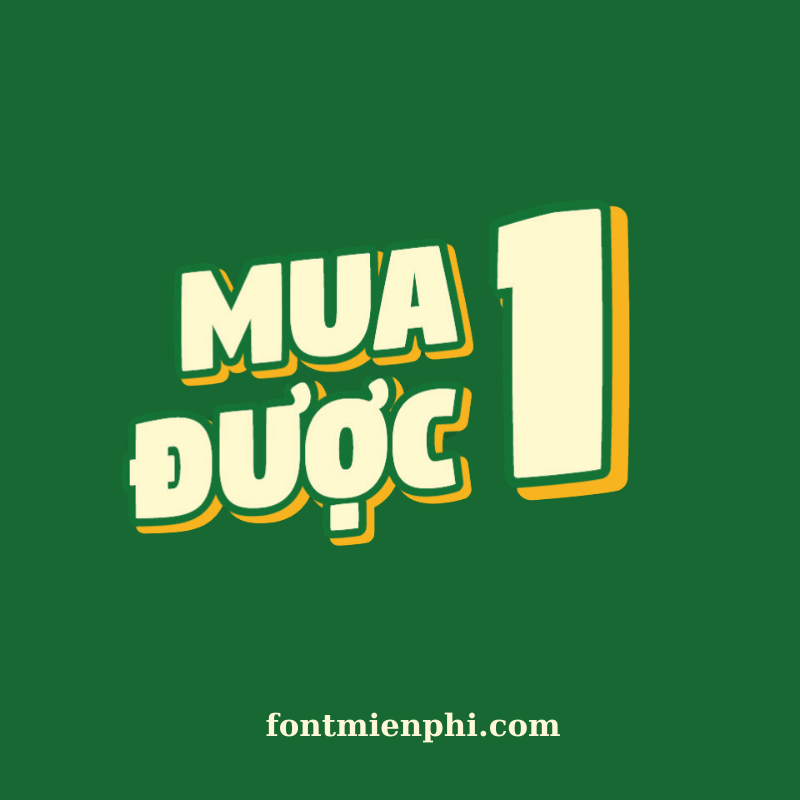
Font Việt hóa 1FTV VIP Digitalt
Font Việt Hóa 1FTV VIP Digital – Phong Cách Độc Đáo Cho Thiết Kế
Giới Thiệu
Font Việt hóa 1FTV VIP Digital là bộ font chữ cao cấp, được thiết kế tinh tế với khả năng hỗ trợ tiếng Việt đầy đủ. Với phong cách hiện đại, đa dạng kiểu chữ, font này phù hợp cho nhiều dự án sáng tạo như thiết kế đồ họa, quảng cáo, in ấn và digital marketing.
Đặc Điểm Nổi Bật
• Hỗ trợ tiếng Việt chuẩn: Đầy đủ dấu và ký tự đặc biệt, đảm bảo tính thẩm mỹ và dễ đọc.
• Đa dạng phong cách: Từ thanh lịch, sang trọng đến cá tính, phù hợp với nhiều ngành nghề.
• Tối ưu cho digital: Thiết kế sắc nét, hiển thị đẹp trên mọi nền tảng số.
Ứng Dụng Font Việt hóa 1FTV VIP Digitalt
1FTV VIP Digital là lựa chọn hoàn hảo cho:
• Thiết kế logo, banner quảng cáo.
• Tạo ấn phẩm truyền thông, tạp chí.
• Thiết kế website, app mobile.
Kết Luận Font Việt hóa 1FTV VIP Digitalt